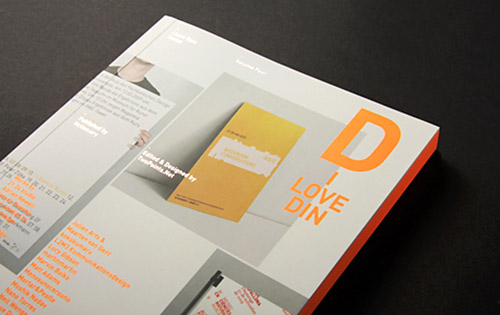
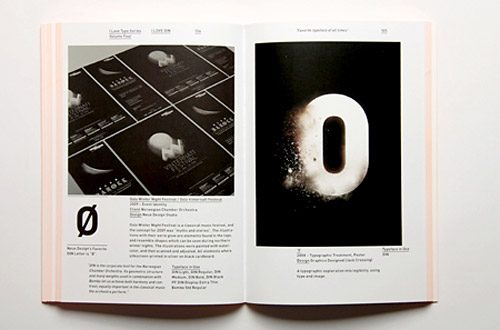
I love DIN ist der 4. Band einer Serie, die sich »I Love Type nennt«. TwoPoints.Net aus Barcelona entwickelt und gestaltet die Buchreihe für den Verlag Viction:ary aus Hong Kong. Zuvor sind bereits erschienen I Love Futura, I Love Avant Garde und I Love Bodoni. Die handlichen Büchlein sind liebevoll ausgestattet, mit Farbschnitt, Leuchtfarbe und geprägter Cover-Typografie. Wer sich tiefer mit der Geschichte einer dieser vier Schriften beschäftigen möchte, erhält ordentlich fundierte Informationen für gut investierte 30 Euro. Dabei geht es nicht nur um die Geschichte der vorgestellten Schriften, sondern auch um wegweisende Anwendungsbeispiele.
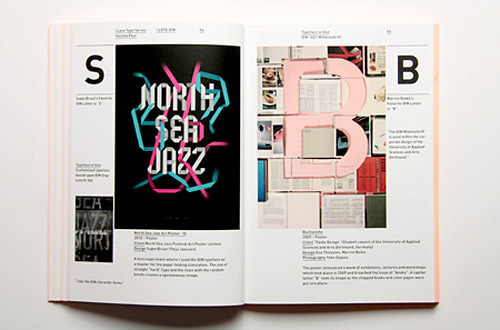
Der Verlag schreibt über die neueste Ausgabe: »Standing for the German national organisation for standardisation, DIN was first introduced in 1923 by Frankfurt foundry, D. Stempel AG, and acclaimed for its legibility and bluntness that would best represent or suit the fields of engineering, technology, traffic and administration. The design later lent the basis for the more recent redesign, FF DIN, followed by a growing popularity with international designers and brands.« Und so kommt natürlich auch »Mister DIN« (so nennen die Herausgeber den FF-DIN-Designer Albert Jan Pool) in einem Interview ausführlich zu Wort.
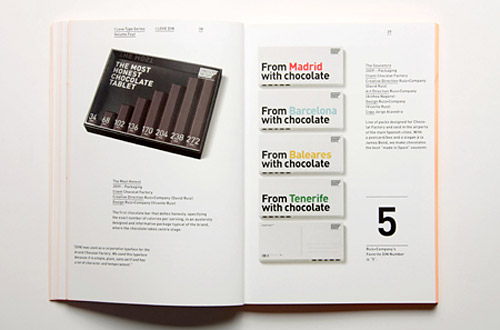
Eine Unmenge von internationalen DIN-Fans haben Beispiele für das Buch zur Verfügung gestellt, darunter Adrian Newell, Atelier Poisson, Birch Studio Ltd., Blotto Design, Blow, Caroline Fabès, Chris Sherron, Commune, Cypher13, designliga, Didier Quarroz at Ecal, Estudio Ritxi Ostáriz, formdusche, Gaël Hugo & Edwin Sberro, George Strouzas, Joe Hinder, Julien Arts & Maarten van Gent, L2M3 Kommunikationsdesign, Lucy Gibson, martinmartin, Marvin Boiko, Moshik Nadav, Nano Torres, Neil Wengerd, Neue Design Studio, Paulus M. Dreibholz, Ragged Edge Design, StudioSpass, Superatelier, SuperBruut, thisislove studio, TwoPoints.Net und Why Not Associates.